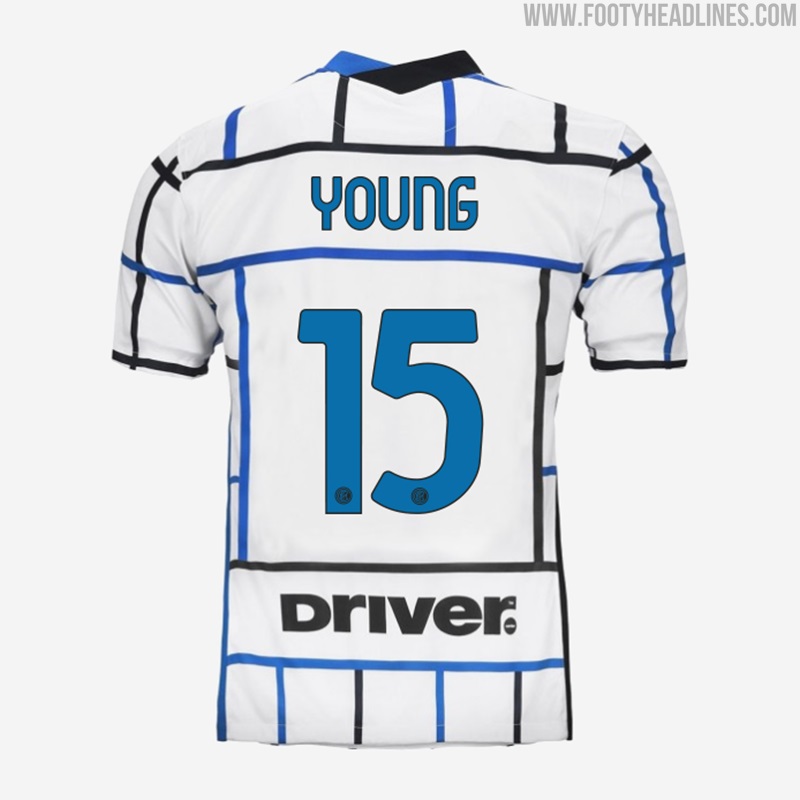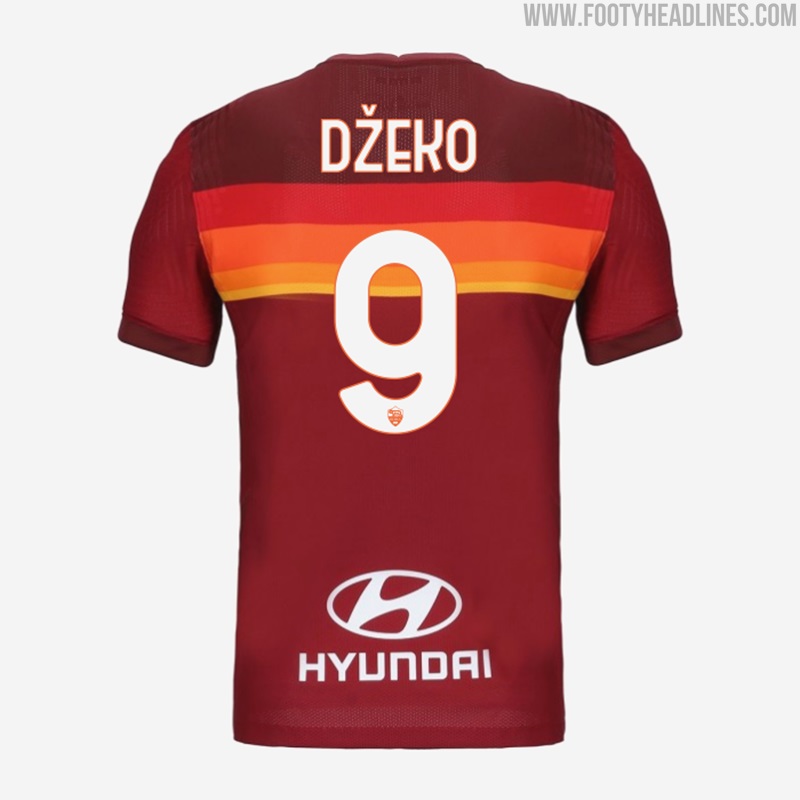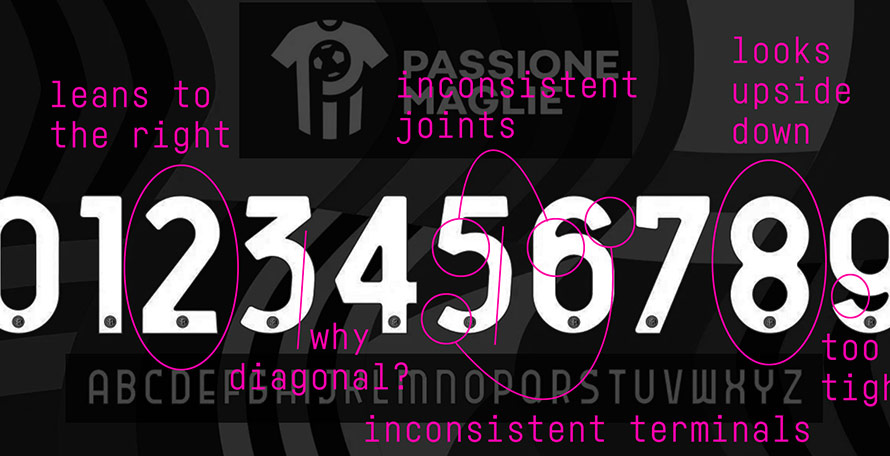
Schriftart-Experte: Deshalb ist die neue Serie A Schrift schlecht
Mit der kürzlichen Veröffentlichung des AS Rom 20-21 Heimtrikots haben wir endlich die Bestätigung der neuen ligaweiten Schriftart für die Serie A erhalten.
Aber ob dir die Idee einer "Eine-für-alle"-Schriftart gefällt - vier von fünf europäischen Top-Ligen haben jetzt eine und nur in der Bundesliga können die Mannschaften immer noch ihre eigenen Designs haben - es besteht kein Zweifel, dass diese Schriftart nicht die beste ist, die es gibt.
Es ist kein Geheimnis, dass wir von Footy Headlines absolut keine Fans davon sind. Aber wenn es sein muss, sollte es richtig gemacht werden. Wir sind der Meinung, dass eine Liga-Schriftart immer versuchen sollte, jegliche Art von Macken oder ungewöhnlichen Designvarianten auf ein Minimum zu reduzieren, um das Aussehen von Trikots nicht zu sehr zu beeinflussen.
Sie ist vielleicht nicht so schlimm wie die von La Liga mit ihren übertriebenen Umrissen, aber die neue Schriftart der Serie A hat eine Reihe von Problemen. Und die gehen über seltsame Buchstaben- und Zahlenformen hinaus, wie ein kürzlich veröffentlichter Tweet des Schriftart-Designers und Experten @sportsfonts_com zeigt:
Wie hervorgehoben, gibt es eine Menge Inkonsistenz mit dem neuen Design und das allein, wenn man sich nur die Nummern anschaut.
- Einige von ihnen sind nach rechts gelehnt, wie die 2, 3 und 5, während die anderen es nicht sind.
- Die Lesbarkeit hätte wesentlich verbessert werden können, wenn man darauf geachtet hätte, dass die Formen nicht zu eng aneinander liegen, wie bei der 6 und 9 zu beobachten ist.
- Schließlich sieht die 8 "auf dem Kopf stehend" aus.
Wir hätten nichts dagegen, wenn die Ligen den Teams wieder mehr Freiheit bei der Wahl der Schriftart einräumen würden - aber was hältst Du davon? Bist Du ein Fan der neuen Schriftart der Serie A und des Konzepts der ligaweiten Schrift im Allgemeinen? Schreib es uns unterhalb.